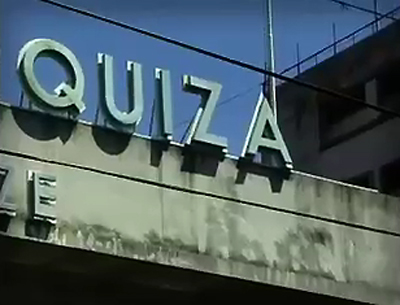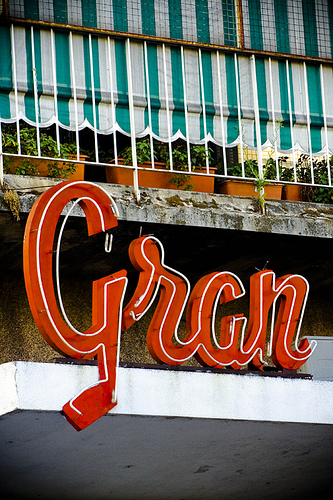
Es frecuente relacionar la tipografía con personas, de hecho las tipografías tienen brazos, ojos, pies, y hasta incluso familias. Por lo tanto no es extraño pensar que «la tipografía de la calle» es una tipografía huérfana, indigente o abandonada. Con lo cual, tampoco es descabellado hacerse preguntas como ¿quiénes son sus padres? ¿porqué la han abandonado? ¿quién la ha dejado ahí? ¿son marginadas? ¿alguien le presta atención? Al igual que sucede con las personas de la calle, probablemente sean demasiadas preguntas y quizás no haya respuestas para todas ellas.
Lo concreto es que están allí, a veces hablándonos, a veces gritándonos, a veces susurrando. Pero…, y si las tipografías gritan… ¿como es que nunca escuché a ninguna?, ¿quienes gritan?, ¿quienes hablan? y ¿quienes susurran?. Y ciertamente no es cosa fácil darse cuenta de esto, pero no imposible; lo que si hay que admitir que en el caso de la tipografía para poder escucharla, extrañamente hay que abrir bien los ojos. Fue entonces cuando decidí salir a la calle con los ojos bien abiertos para poder escuchar mejor; estaba absolutamente convencido que de esta manera iba a poder encontrar el estilo que la definiera. Luego de un buen tiempo de escuchar tipografía, había logrado obtener un excelente oído visual para la tipografía de la calle; pero, todavía no había podido lograr encontrar el tan ansiado estilo que la definiera. Es por eso que decidí volver a las fuentes y comparé nuevamente a la tipografía con las personas, fue entonces ahí cuando encontré el estilo, el estilo de «la tipografía de la calle» es exactamente el estilo de nuestra sociedad, es decir, es un reflejo de lo que somos.
Somos limpios, pero también somos sucios. Hay gente ordenada, gente que no lo es tanto. Somos tristes y a veces alegres; somos altos, bajos, gordos, flacos, negros, blancos, y podría seguir escribiendo infinidad de adjetivos mas. En definitiva, la calle es el lugar donde se hace evidente todas esas cosas que somos, y la tipografía es un excelente medio para representarnos. De hecho que ¿Quién no ha salido a la calle y se ha encontrado con una «Q» de Bodoni cruzando la esquina? o ¿Quién no ha pasado por la vereda de un bar y ha visto como una «s» de Garamond compartía un café con una «T» de Helvetica Compressed? Pero, ante tanta diversidad, como es posible planificar una tipografía de la calle? Ciertamente es difícil diseñar y planificar la tipografía de la calle, o el estilo tipográfico que queremos para nuestras calles, ya que en cierta medida estaríamos diseñando o planificando nuestra sociedad.
Quizás allí radique el error, estamos acostumbrados a diseñar logotipos, folletos, revistas, catálogos, nunca tuvimos un cliente que nos diga «Sr. queremos diseñar las calles» o «Tenemos intenciones de rediseñar la sociedad». Hoy por hoy nuestras calles son una excelente muestra de que no hemos estado pensando en esto últimamente. Basta tan sólo con recorrer unas pocas cuadras y podremos ver como una misma información puede estar representada de diferentes maneras. Por ejemplo, el número de la calle de un edificio no puede estar representado por una tipografía «distinta» o «moderna», pues muy probablemente no todos los que vivan en el edificio sean «distintos» o «modernos». Pero de lo que si podemos estar seguros que todos los habitantes del edificio son parte de nuestra sociedad. La tipografía de la calle no puede ser una simple representación del estado de ánimo o capricho del diseñador gráfico de turno, sino que tiene que ser una representación fiel de lo que anhelamos como comunidad; pues de hecho, eso es la calle, nuestra comunidad; es decir, es de todos, pero de nadie en particular.
¿Y cómo es una tipografía que represente fielmente el anhelo de nuestra sociedad? Como primera medida deberíamos partir de un brief, cosa que escasea bastante, y mas aún tratandose de nuestra sociedad; pero, si nos ponemos a pensar, no es muy difícil definir el brief ya que todos estamos inmersos en esta sociedad y en mayor o menor medida sabemos qué está mal, qué está bien, y qué podría estar mejor. A partir de este brief, y evitando los estados de ánimos, caprichos y modismos; y sobre todas las cosas con mucha dedicación, seguramente llegaremos a una representación fiel de nuestro anhelo. Debe ser clara, concisa, efectiva, en otras palabras: «funcional». Y cuando hablamos de funcionalidad, quiere decir que, debe comunicar ni más ni menos que lo que debe comunicar. Para ello deberemos tener en cuenta 2 factores fundamentales: ¿Quiénes leeran esta tipografía? ¿Bajo qué circunstancias?
¿Quiénes la leeran? ya hemos hablado del tema, somos todos; desde el intendente de la ciudad hasta el vendedor de puestos de diarios, pasando por el ingeniero civil, el analista de sistema, la secretaria, el colectivero, etc… Quizás la parte mas compleja sea desarrollar una tipografía que funcione bajo las distintas circunstancias en las cuales puede encontarse un lector. Sin ir mas lejos, no es lo mismo tener que leer el nombre de una calle desde el colectivo en movimiento que caminando tranquilamente por la vereda. Un caso crítico, pero no poco frecuente: Un lector cansado y posiblemente con poco tiempo para leer. ¿Quién no ha vuelto de trabajar agotado? Ocho o diez horas frente a una computadora, una carrera de 30 metros con obstáculos para alcanzar el colectivo, y al fin… un asiento. Naturalmente, es un lector cansado y es probable que se quede dormido. Pero esa no es la situación crítica, la situación crítica comienza cuando el lector abre los ojos, y ciertamente desea saber donde está. Es aquí donde nuestro trabajo puede resolverle o no el problema en el cuál se encuentra. Si diseñamos una tipografía de contraformas no muy claras o cerradas, indudablemente le llevará mucho mas tiempo poder diferenciar un caracter de otro. Por eso, debemos poner especial énfasis en la contraforma de los caracteres, ya que una letra se diferencia de otra no sólo por su forma sino que también por su contraforma.
Esto no quiere decir que la contraforma es mas importante que la forma ni viceversa, sino que, debemos lograr un equilibrio entre una y otra. Otro factor que no podremos pasar por alto es el espaciado rítmico a utilizar, esto implica poner especial atención en el tracking (interletrado), kerning (ajustes visuales sobre pares o tríos de caractéres) e interpalabra. Un buen espaciado rítmico es aquel que ante una palabra o frase no presenta sobresaltos y permite leer con claridad desde principio a fin. En definitiva, creo que el diseño de la tipografía de la calle está sujeto y debe desarrollarse en función de este tipo de situaciones críticas en las cuales puede encontrarse el lector, lo cuál demuestra una vez más que la solución está dentro del mismo problema. Por lo tanto, cuanto más nos involucremos en el problema, estaremos más cerca de encontrar la solución. Una vez que tengamos esa tan ansiada tipografía que nos represente fielmente, y al mismo tiempo funcione para lo cual ha sido concebida, simplemente estará en nuestras manos la responsabilidad de respetarla y hacerla respetar como un integrante mas de nuestra sociedad.
Es por eso que está en nosotros, los diseñadores, la voluntad de empezar a plantear una calle que susurre, hable o grite. Y también está en nosotros la responsabilidad de que por lo menos la tipografía de la calle se asemeje al futuro que queremos como sociedad.